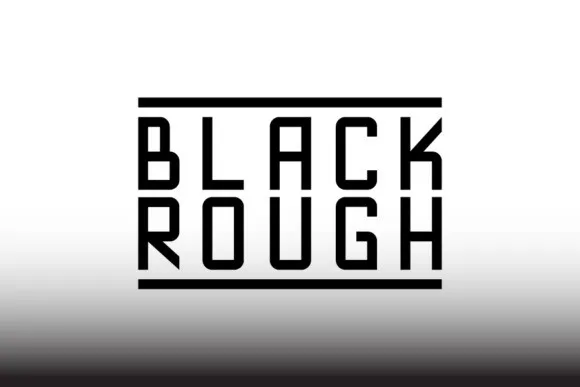
Blackrough Sans Serif Font
Descubra Blackrough Sans Serif Font, uma elegante sans serif moderna com um design marcante. Criada pelo designer Hamilton para Sign Studios, a Blackrough é perfeita para criar desafios de identidade visual que chamem atenção, como logotipos fortes e cartões de visita. Com linhas poderosas e texturas autênticas, essa fonte convida você a explorar seus traços únicos e icônicos. Ideal tanto para design de logotípicos impressionantes quanto para posters que atraiam atenção e outros materiais em geral, a Blackrough é perfeita para quem deseja destacar-se. Suas formas de letra fortes garantem um impacto inegável em seus designs, mantendo o seu compromisso com uma elegância distinta. Experimente sua fonte única agora e inspire-se com o poder da Blackrough Sans Serif!